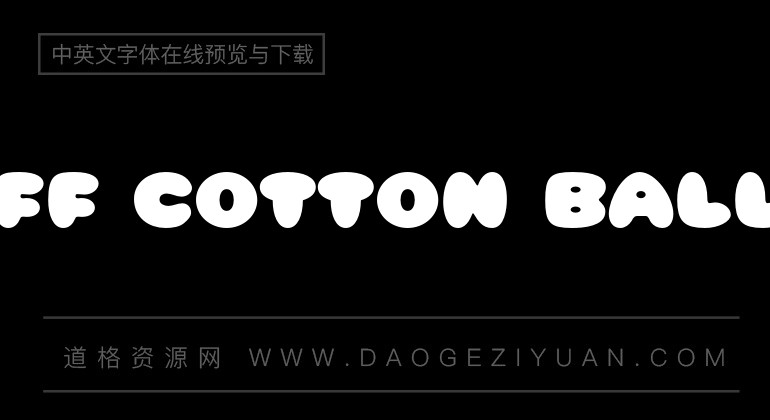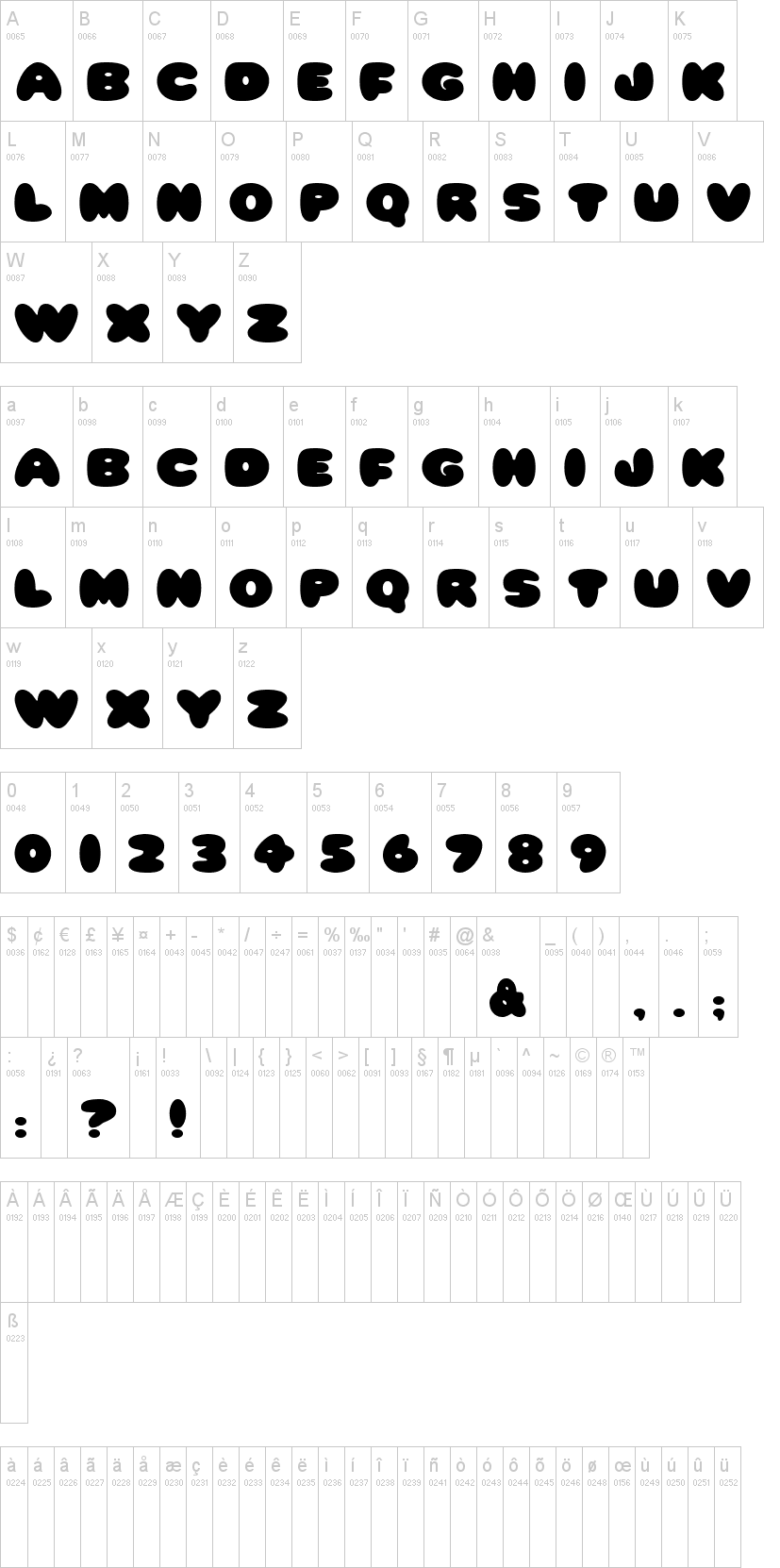
HFF Cotton Balls
HFF Cotton Balls 是一款易读的曲线体字体,它由哈佛学院的设计师Hugh Frazer发明。它的字体风格清新,曲线流畅,具有良好的可读性,可以用于商业设计、网页设计、广告设计等。HFF Cotton Balls 字体拥有英文字母、数字、标点符号、特殊符号和拉丁文字符号,可以满足您的各种设计需求。
HFF Cotton Balls是一款非常不错的手写艺术字体,具有很好的视觉感,适合于文化类的宣传设计、商业类品牌的广告和产品包装设计以及个性化文字排版等较多场景。
HFF Cotton Balls字符映射图